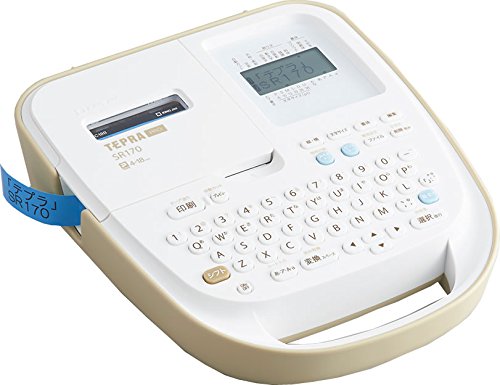
ラベルライター「テプラ」PRO SR170
株式会社キングジムによるラベルライター「テプラ」PROシリーズから新製品として、てがき書体や可愛らしい絵文字、外枠などを搭載し今まで以上にデザイン性の高いラベルが作成できる「SR170」が4月27日に発売になる。
ラベルライターとは、任意の文字や画像を、テープ状のシールに印刷する機器で、「SR170」は、同社が販売している従来機種「SR150」に比べて、最大印刷可能幅は9.0mmから13.5㎜に拡大し18mm幅テープでは最大6行まで印刷が可能になっている。また、文字サイズも6段階へと進化し、より大きな文字が印字可能になった。
その他、「テプラ」シリーズ初の機能として「お名前タグ」印刷機能や「ピッとコード」印刷機能を搭載した。
「ピッとコード(iOSアプリ:無料)」印刷機能は、文字の前や後ろに専用の二次元コード「ピッとコード」を印刷できる機能で、iOS専用アプリを使うと、iPhone内の写真やメモなどのデータを「ピッとコード」に紐づけことができる。紐づけしたデータは、専用アプリで「ピッとコード」を読み取るだけで簡単に呼び出せる。
ラベルライター「テプラ」PRO SR170
ビットマップフォントが採用
種類はゴシック体/明朝体/てがき体の3書体